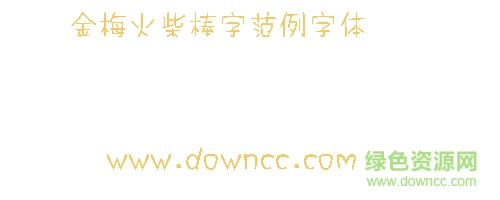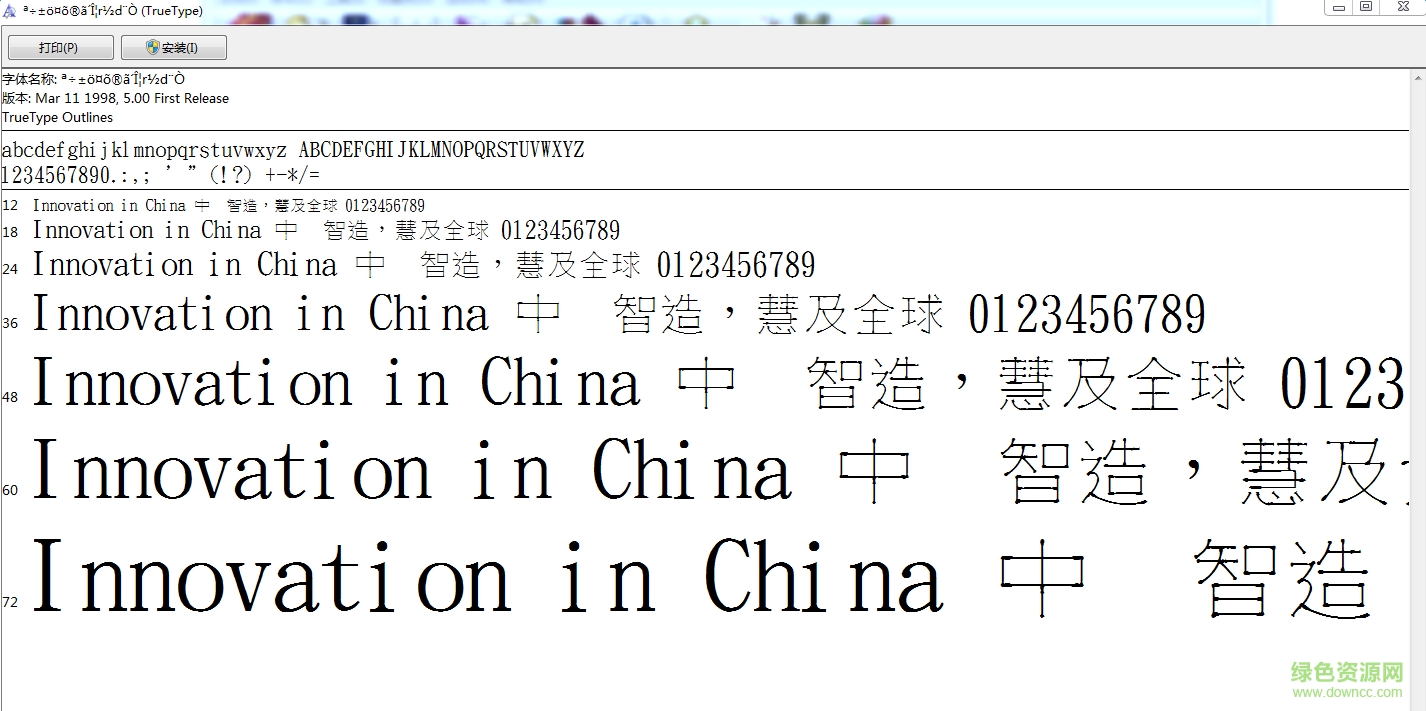
金梅火柴棒字范例字體是一款金梅類細(xì)長(zhǎng)字體軟件,火柴棒的字體給人非常纖細(xì)的感覺(jué),深受廣大書法家喜歡,還有更多好看字體盡情期待,歡迎到綠色資源網(wǎng)下載體驗(yàn)!
該字體線條由一根根火柴棒組成看上去較細(xì),字形端莊雄秀,神韻超逸,看上去十分美觀,整體效果非常統(tǒng)一,且字庫(kù)完整,可以廣泛應(yīng)用于廣告設(shè)計(jì)、新聞媒體、宣傳海報(bào)、ppt、影視制作以及內(nèi)容用字等領(lǐng)域,
金梅火柴棒字范例是一款金梅類火柴棒樣式字體,字體效果比較細(xì)長(zhǎng),喜歡細(xì)長(zhǎng)字體的朋友可以下載使用看看效果如何。